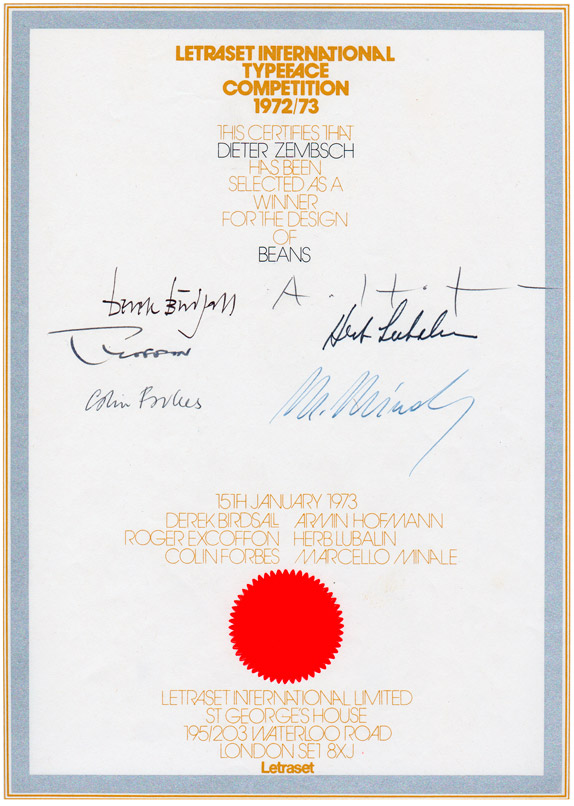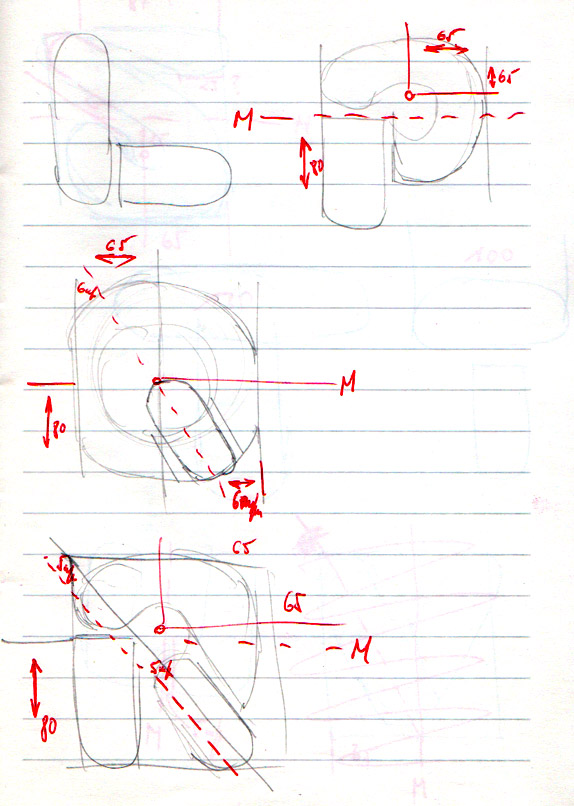
It is not often that we are overwhelmed by a font proposal, pitched to us out of the blue, by a stranger speaking in an odd dialect. But it can happen. And it did happen a few months ago when Charles Grant, hailing from Macclesfield near Manchester, England, approached us with sketches of a strangely familiar font. Could it be Mecanorma, Letraset, Zipatone, Dover, Solotype? Turns out it was Letragraphica: «BEANS», the winning entry by German-born Dieter Zembsch in Letraset’s International Typeface Competition for 1972/73.
Just in time for the font that set up this career to re-appear in a new incarnation, 25 years down the line - hopefully again boosting the career of a promising young designer. Having gained valuable experience working on the digital version of «BEANS», Charles Grant is already working on another Zembsch classic - the formally related and equallly rare «Jumping Jack», originally released by Mecanorma not long after Mr. Zembsch had won the Letraset competition.
Das sah im ersten Moment aus wie eine kaputte »Kada«, welche ja aus dem gleichen Hause stammt. Finde die Beans etwas unnötig, denn mit der Kada hat man bereits einen nahezu identischen Headline-Font, der auf mich in sich geschlossener und »runder« wirkt.
seh ich ganz genauso - ehrlich gesagt war ich
etwas entsetzt als ich die beans gesehen habe.
Ach, das sind Buchstaben? :lol: besonders gefällt mir das A :mrgreen:
Zwischen R und F ist da so was… könnte ein kaputtes N sein oder ein A :hammer:
Na wenigstens gut ausgebaut scheint die Schrift zu sein. Es scheint einen kyrillischen Zeichensatz zu geben. Zumindest ein kyrillisches I (?) ist vorhanden.
Da haben sie das Dingsda, das Bertel als mögliches A identifiziert hat, gespiegelt. So sieht es tatsächlich etwas A-ähnlicher aus.
Zwischen R und F ist da so was… könnte ein kaputtes N sein oder ein A
Vom Sinn her sollte man zwar ein A erwarten, aber was da steht, ist bestimmt keines. Da muss sich jemand vertippt haben.
Das A haette ich eher fuer einen Warnhinweis gehalten:
Finger weg, sonst Finger weg :hammer: